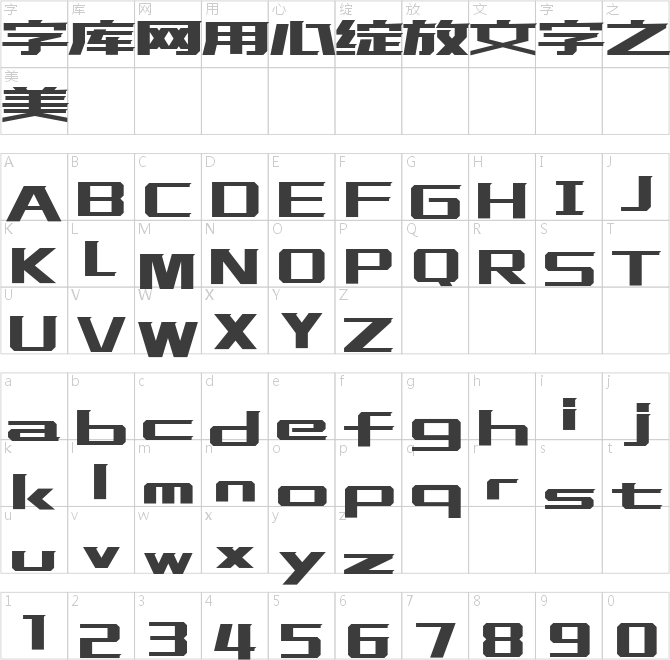
设计师爱心体1号字
【设计师爱心体1号字】
【设计师爱心体1号字】基于中华人民共和国GB2312-80字符集汉字部分标准,TrueType格式,共收容汉字6763个,英文及标点等常用字符251个。
【作者信息】
设计师爱心体1号字设计师团队:
刘兵克、李买、刘金营、刘志明、班小许、熊伟、周登恒、高晗、符重庆、李雪萍、武瑞鑫、黄婕妮
【关于困境儿童】
《设计师爱心体1号字》是为了能够更好地服务困境儿童,让他们的未来有更多的可能性,弥补他们学习生活中艺术教育的缺失,字体设计师刘兵克与历下区未成年人救助保护中心合作,为历下区困境儿童设立设计师公益基金,于20216月发布。
【关于设计师爱心体1号字】
设计师爱心体,源自“困境儿童”公益活动。由设计师刘兵克发起这个项目,并设计最初的字形规范及基本部首,最终,一套好用且免费的中文字体“设计师爱心体1号字”诞生,并在20216月发布。
在未来的日子里,刘兵克将会带领他的团队持续开发多套字库作品,设计师爱心体1号字只是开始,未来会出现设计师爱心体2号字、3号字、4号字、5号字……而每一套爱心字库,将会帮助和捐助予不同的受助对象。
“设计师爱心字库,一方面可以让设计师有更多的字库选择,另一方面,也让大家通过对爱心字库的捐助与下载,为公益事业献上爱心,这是一件美好和温暖的事情。我非常期待1号字能够得到大家的认可,说实话,也更期待1号字能完成目标捐款金额。如果能够顺利完成,这会给我们带来更大的勇气和信心,爱心字库这份事业,我们会更有劲头的做下去!”
刘兵克